Mới đây, Microsoft đã công bố kế hoạch thay đổi lớn cho bộ ứng dụng Office. Cụ thể, hãng dự định sẽ chọn font chữ mặc định mới cho Microsoft Word, Excel, PowerPoint. Như vậy có nghĩa là font Calibri đã được sử dụng gần 15 năm qua, từ phiên bản Microsoft Office năm 2007 sẽ được thay thế.
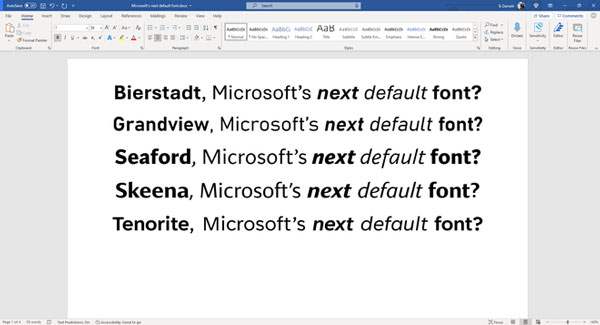
Theo The Verge, Microsoft đã chọn các nhà thiết kế tạo ra 5 font chữ dạng không chân (sans-serif) sau đó đưa ra để thu thập ý kiến. Cuối cùng, hãng sẽ chọn một font làm mặc định cho toàn bộ ứng dụng Office vào năm 2022.
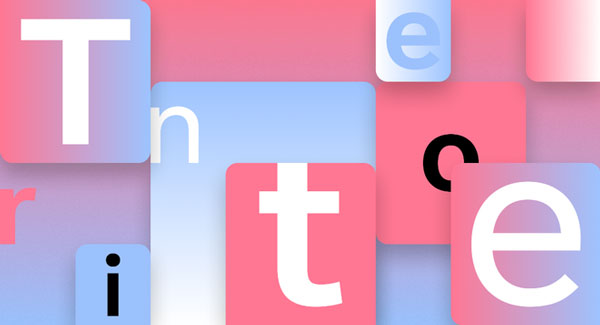
Font Tenorite được thiết kế bởi Erin McLaughlin và Wei Huang, mang các đường nét truyền thống. Font chữ này có chiều dài ký tự rộng, dấu câu đậm và rõ ràng, được coi là phiên bản hiện đại hơn của Times New Roman.
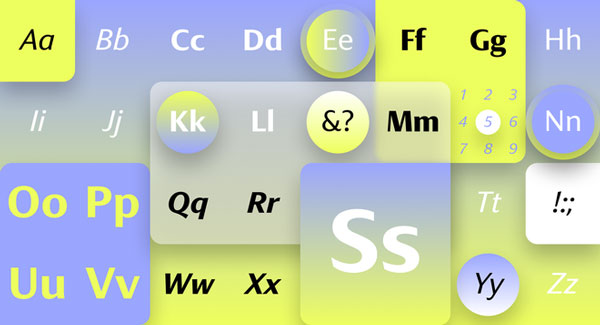
Font Skeena với nét thanh đậm rõ ràng, một số chữ như S, A và J sở hữu được cong mạnh, là sự kết hợp từ các xu hướng thiết kế font trong lịch sử. Font chữ này được thiết kế bởi John Hudson và Paul Hanslow.
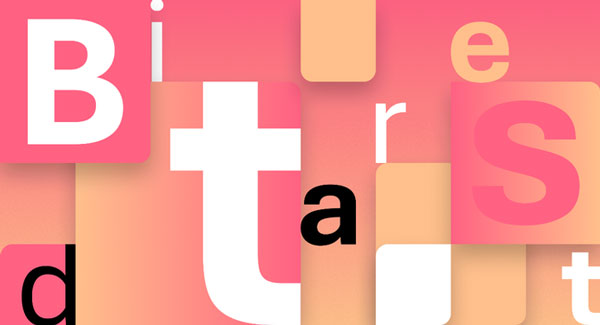
Font Bierstadt hay còn gọi là grotesque san-serif với nét cuối của các chữ được thiết kế dứt khoát nhưng vẫn mềm mại với một số đường cong. Đây là sản phẩm của Steve Matteson được lấy cảm hứng từ kiểu chữ Thụy Sĩ giữa thế kỷ XX. Matteson đặt tên font là Bierstadt, theo tên một ngọn núi ở Colorado (Canada).
Font Seaford mang phong cách cổ điển, biến tấu từ kiểu chữ có chân (serif) được tạo ra bởi 3 nhà thiết kế Tobias Frere-Jones, Nina Stössinger và Fred Shallcrass. Seaford là font chữ được The Verge đánh giá là mang cảm giác thoải mái nhất khi đọc các tài liệu dài.
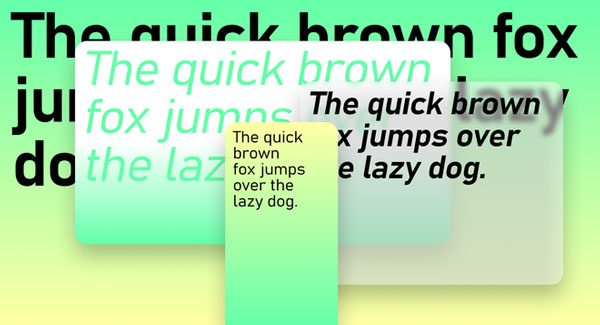
Font Grandview được tạo ra bởi Aaron Bell, lấy cảm hứng từ biển báo giao thông cổ điển của Đức. Kiểu chữ này được thiết kế dễ nhìn, tạo sự thoải mái khi đọc các văn bản dài. Grandview được đánh giá là font chữ nổi bất nhất trong 5 kiểu chữ mới được Microsoft giới thiệu.
Microsoft đã cập nhật các font chữ mới trong dịch vụ Microsoft 365 để người dùng trải nghiệm và bình chọn. Sau đó, Microsoft sẽ lấy một font phù hợp nhất để thay cho Calibri từ năm 2022.